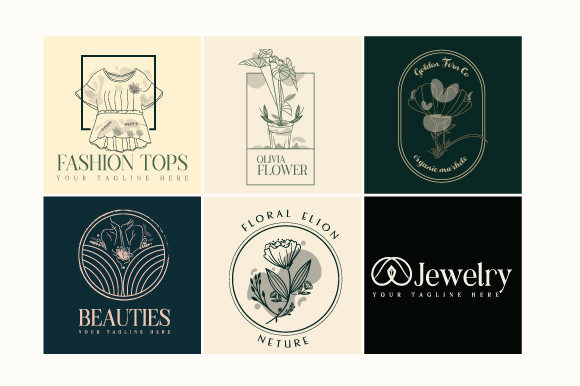
Botanical Bundle Pack
การค้นหาองค์ประกอบการออกแบบที่เหมาะสมอาจเป็นเรื่องท้าทาย แต่ Botanical Bundle Pack นำเสนอคอลเลกชันที่โดดเด่นซึ่งช่วยยกระดับงานของคุณได้ทันที
ไม่ว่าคุณจะสร้างผลิตภัณฑ์ POD (Print on Demand) คำเชิญงานแต่งงาน หรือกราฟิกโซเชียลมีเดีย Botanical Bundle Pack ก็เหมาะสมอย่างยิ่ง